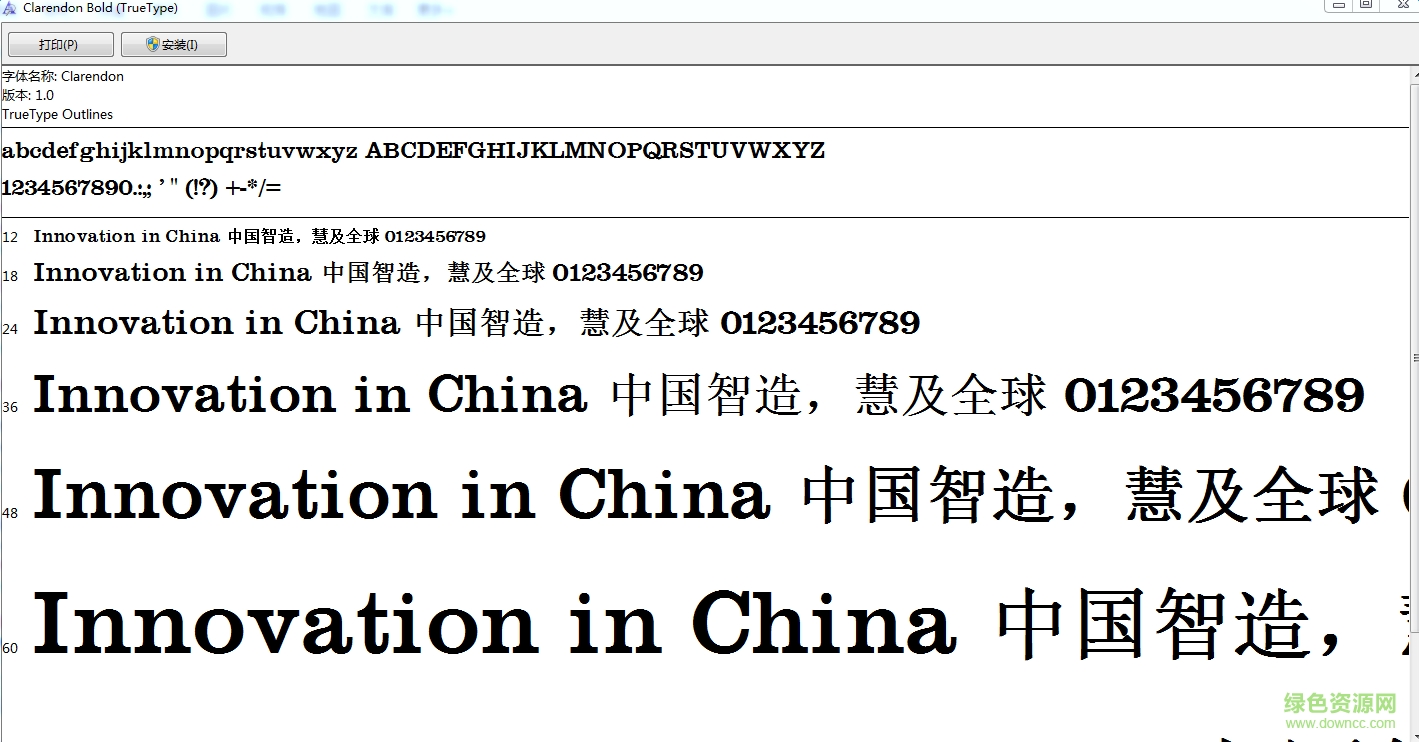
clarendon字體是一款粗襯線英文字體,又稱埃及體,該字體字型粗黑,筆畫粗細(xì)差距,線條弧線獨(dú)具特色,常常用于各種書刊、雜志、海報(bào)的標(biāo)題設(shè)計(jì)方面,喜歡就來綠色資源網(wǎng)下載吧!
在字體排印學(xué)中,粗襯線體是一種襯線字體,其襯線比一般來的粗黑,所以常被使用于報(bào)章雜志或是廣告的標(biāo)題,而非內(nèi)文。這類字體通常被說成是單純?cè)?a href="http://573ee.cn/k/wuchenxianziti/" target="_blank">無襯線字體加上大襯線,因?yàn)樽帜副旧淼男螤詈蜔o襯線體很類似,筆畫的粗細(xì)幾乎沒有差別。